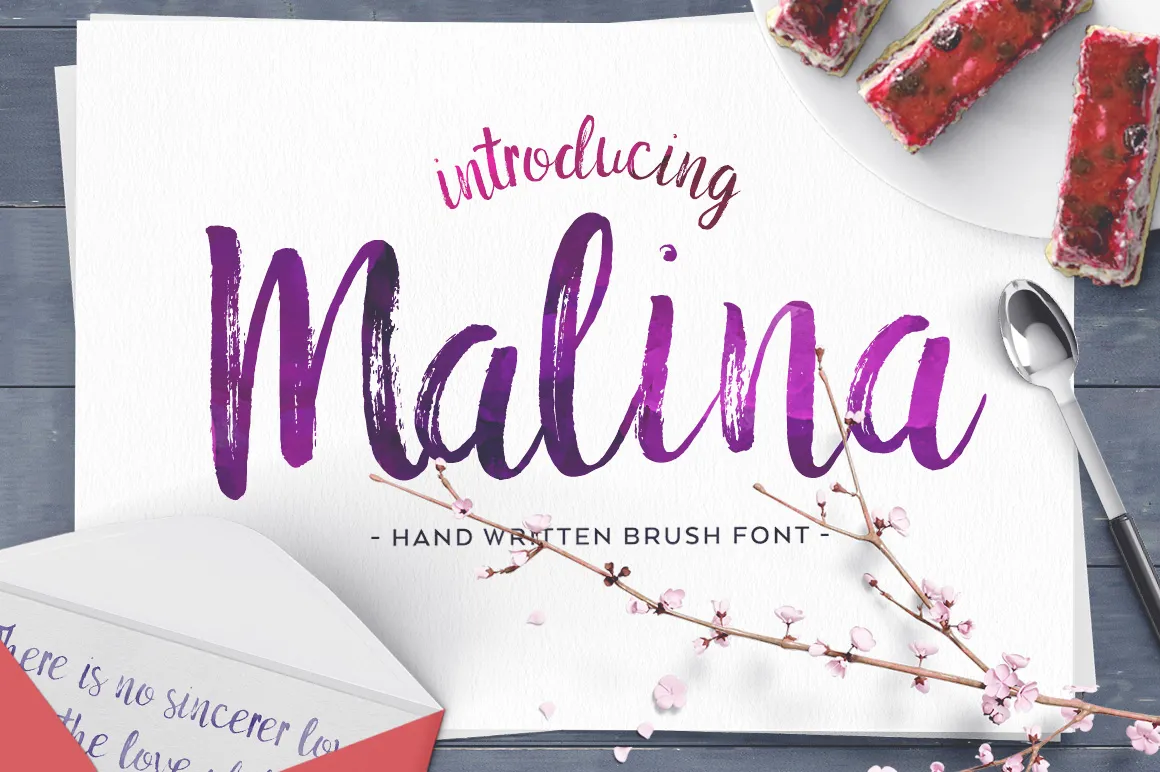
Malina Brush Font – Fonte Grátis
Malina Brush Font
A Malina Brush Font é uma fonte de traços grossos e elegante criada especialmente para quem valoriza a mão-direita no design digital. Seu designer Hamilton introduziu uma mistura única de suavidade e força nas letras, resultando num estilo que é tanto alegre quanto sofisticado. Com traços redondos e finos, essa fonte consegue transmitir emoção sem perder o controle gráfico necessário para projetos variados como logotipos, headlines ou até mesmo designs digitais de arte livre. Ela foi criada pensando em designers que buscam um equilíbrio entre a natureza dos traços grossos e a eficácia da tipografia digital. E o melhor? Com esse cupom especial para os assinantes do 2015 Year Bundle, você pode ter essa fonte gratuita por tempo limitado. Não perca esta oportunidade de adicionar um toque autêntico à sua próxima criação.